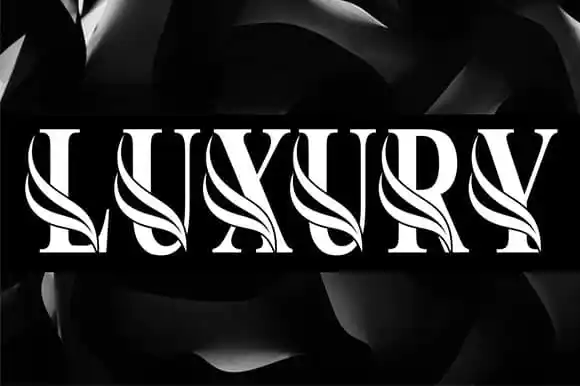
Luxury Display Font – Fonte Grátis
Luxury Display Font
A fonte Luxury Display é perfeita para projetos requintados e sofisticados que necessitam de uma escrita com toque artístico. Esta elegante serif font destaca-se quando usada em aplicativos como displays na parede, convites de casamento, logotipos para posts nas redes sociais, anúncios, embalagens de produtos, designs de produtos, rótulos, fotografia e até mesmo marcas e material de escrita. Seja para projetos comerciais ou pessoais que exijam um toque a mais de sofisticação, Luxury Display é uma escolha óbvia para garantir que seu design seja impecável e com toque refinado. Esta fonte serifa não apenas eleva o nível visual dos seus trabalhos, mas também oferece a oportunidade de transmitir elegância e classe em cada projeto.